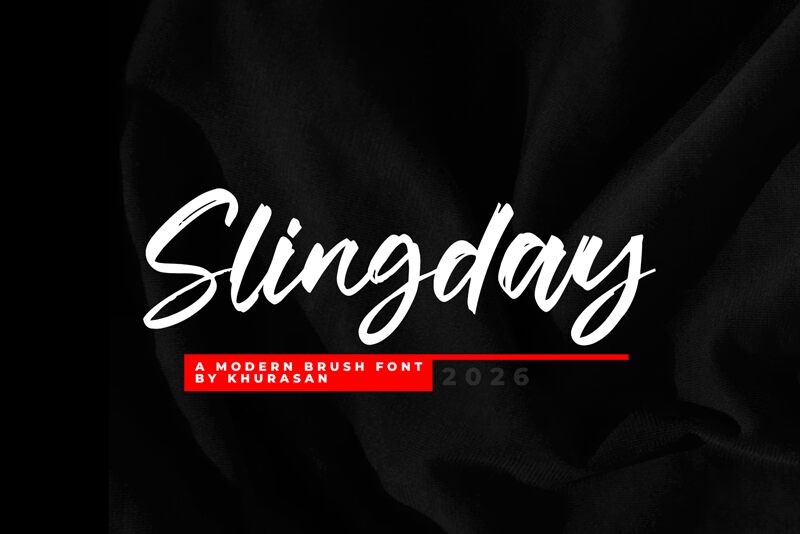
Slingday di Khurasan è un font brush gratuito, caratterizzato da tratti lunghi e veloci che si slanciano verso l'esterno per poi chiudersi in curve decise. Questo ritmo vivace conferisce alle lettere uno stile calligrafico, con giunzioni fluide e volute estese che mantengono un'ottima espressività senza apparire eccessive.
È ideale per loghi, packaging, menu di caffetterie, inviti e intestazioni per i social media, dove una linea script dinamica può definire il layout. Le aperture allungate e i passanti pendenti lasciano respirare le parole brevi, rendendo Slingday perfetta per firme, branding nel settore beauty o etichette dallo stile boutique.